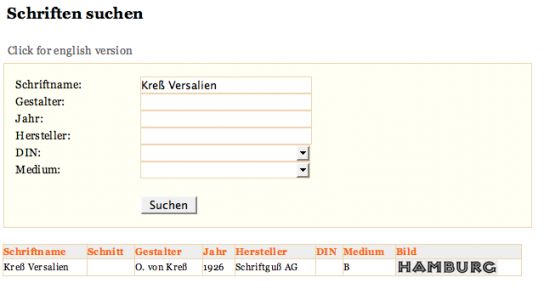
Kress Versalien
For the Kress-Versalien I don't know, just a few hints where you probably get your answer (if you don't get the answers here …)
Lars Kähler runs Global-Type.org the digital Seemann-Fontbook. It recognizes the search-term, but doesn't display anything unfortunately.
Or try Georgs Bleisetzer.de Forum to ask about it. He is still on vacation but I think he said he logs in from time to time.
I didn’t know about Global type yet. Here the designers name is O. Von Kress and the year of release 1926.
The website below credits Oskar Kress von Kressenstein (no date given).
http://www.librocist.org/blei/typen.htm
In the book Deco Type, stylish alphabets of the ‘20s & ‘30s the designer is called Oskar Kress and the year of release of the typeface is dated 1929.
Other sources, which I can’t find on the web anymore were talking about Otto von Kress and gave 1923 as date of release. Very confusing.
I was hoping that maybe someone on this forum could give more information from period sources, but if not, Bleisetzer will maybe be my last hope.
It is a possibility, that Mr. Kress droped his nobility and/or the title in the1920s or 1930s . That was not unusual.
Mit dem Untergang der Monarchie in Österreich-Ungarn wurden nach dem ersten Weltkrieg alle Adelstitel in Österreich abgeschafft.
Daher Dietmar (Edler von) Schönherr , Otto (von) Habsburg.
Ausnahme Herbert von Karajan (Künstlername)
In meinen Unterlagen heißt der Entwerfer
Oskar Freiherr von Kreß. Schrift erschien 1926.
Erste Abbildung im Seemann Nachtrag von 1927.
Näheres ist über den Schriftentwerfer nicht bekannt. Evtl. könnte man über den Adelstitel (Gotha's Adelsverzeichnis oder ähnliches) etwas finden über die Familie.
I didn’t know about Global type yet. Here the designers name is O. Von Kress and the year of release 1926.
@ Schwalbenkönig: Der record kann natürlich nur dargestellt werden, wenn er gefunden wird. Dann erscheint auch das Bild, oder nicht?
Nochmal, leider nein.
ich gebe zum Beispiel ein: »Kreß«, denn vervollständigt die DB automatisch auf sowas wie »KreÄY Versalien«. Aha, denkt man sich da, die DB hat da was in ihrem Fundus. Dann bestätigt man diesen automatisch vervollständigten Suchparameter und dann kommt unten als Ergebnis nur der lapidare Satz »Keine gefunden«.
Weder ein Eintrag, noch natürlich auch kein Bild dazu.
Leider. (Siehe abermals den Screenshot oben …)
EDIT: Habe ihn dummerweise im falschen Posting eingefügt, sorry, hier also nochmal:
Achsoja, falls das für dich von Interesse ist, Lars: ich verwende hier Safari 2.0.4 (419.3) auf MacosX 10.4.9 (G5)
Hier exakt die gleiche Safari-Version, OS schon auf 10.4.10. Das wird es wohl kaum sein. Ehrlichgesagt habe ich da keine Idee im Moment. Aber vielleicht jemand anders? Und ich werde das mal Thomas berichten (dem Programmierer), der aber ohnehin kein Safari auf seinem XP hat – ich teste ja immer für ihn auf dem Mac.
Thanks for clarifying this. While we are at it, as far as I know Schriftguß has had several company names, do you know when these name changes took place? Below is my list as far as I could find:
- Brüder Butter
- A.G. für Schriftguß
- Schriftguß A.-G.
- Schriftguß K.G. (1945?–1948)
- VEB Schriftguß Dresden (1948–1951)
- VEB Typoart (1951–1989)
- Typoart GmbH (1989-????)